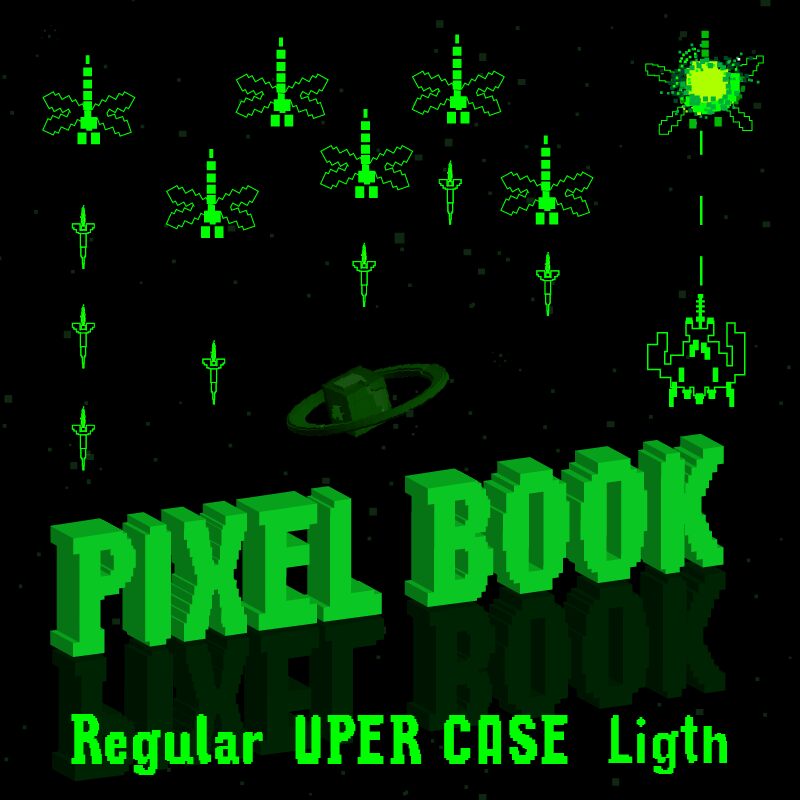
Pixel Book CL od Galdino Otten je bezplatné digitálne displejové písmo s výrazným bitmapovým charakterom a jemne literárnym nádychom. Písmená pôsobia vysoko, blokovo a zámerne odstupňovane, pričom spájajú tuhé pixelové hrany s niekoľkými zúženými tvarmi, ktoré dodávajú textúre menej mechanický vzhľad.
Hodí sa na titulky plagátov, grafiku retro hier, úvodné karty, obálky zinov a obaly, ktoré si vyžadujú atmosféru raných obrazoviek bez toho, aby pôsobili príliš arkádovo. Ako bezplatné písmo funguje najlepšie v krátkych displejových ukážkach, kde vyniknú masívne vertikály a štvorcové rezy, najmä pri logách alebo titulkoch, ktoré potrebujú ostrý, kódovaný rytmus.